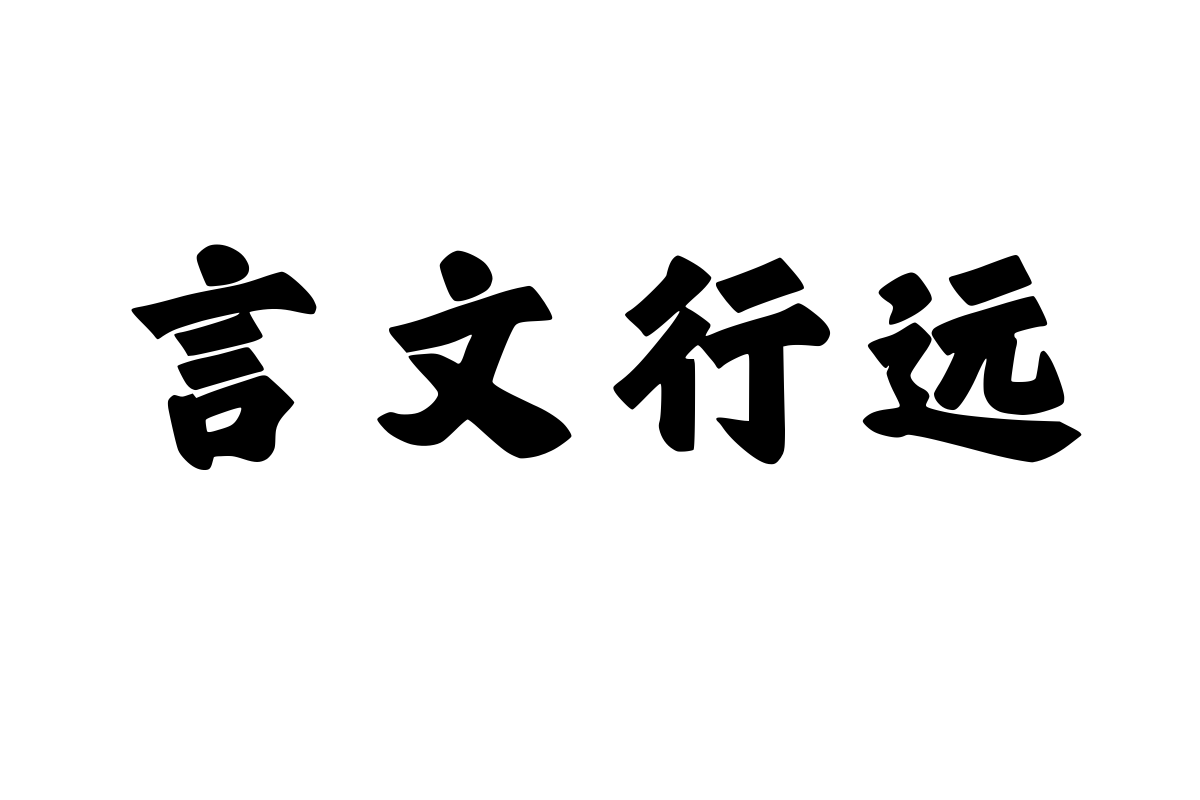
汉呈摩崖石刻体是中国古代的一种字体,主要流行于汉代至唐代。这种字体的特点是笔画粗细变化较大,线条流畅自然,具有很高的艺术价值。
汉呈摩崖石刻体的字形结构较为简单,主要由横、竖、撇、捺等基本笔画组成。其中,横笔和竖笔的粗细变化较大,形成了强烈的视觉效果。撇和捺的笔画则相对较短,使得整体字形更加简洁明了。
在书写过程中,汉呈摩崖石刻体注重线条的流畅性和力度感,通过不同的笔画粗细变化来表现不同的情感和意境。这种字体的书写速度较快,适合用于表达激昂、热烈的情感。同时,由于其线条流畅自然,也适合用于描绘山水、花鸟等自然景观。
总的来说,汉呈摩崖石刻体是一种具有很高艺术价值的古代字体,它不仅体现了古人对于汉字美学的追求,也为后世留下了丰富的书法资源。